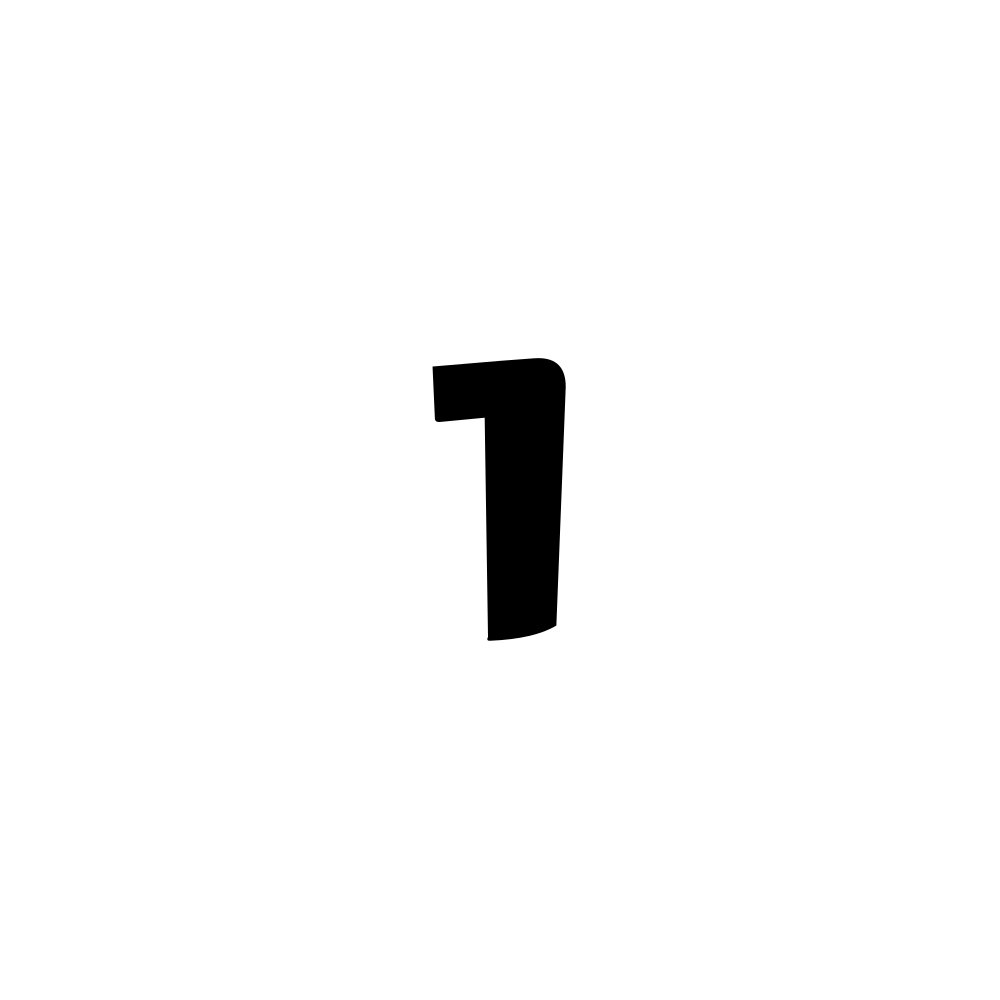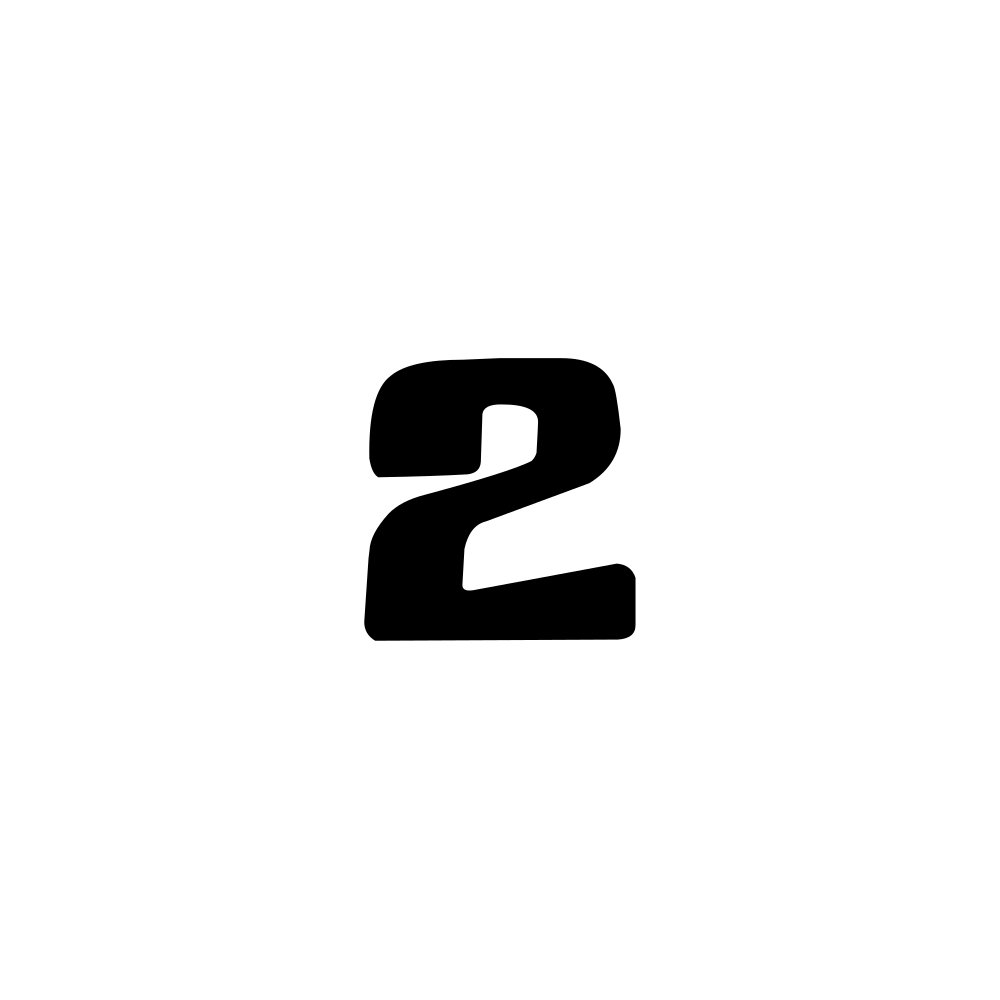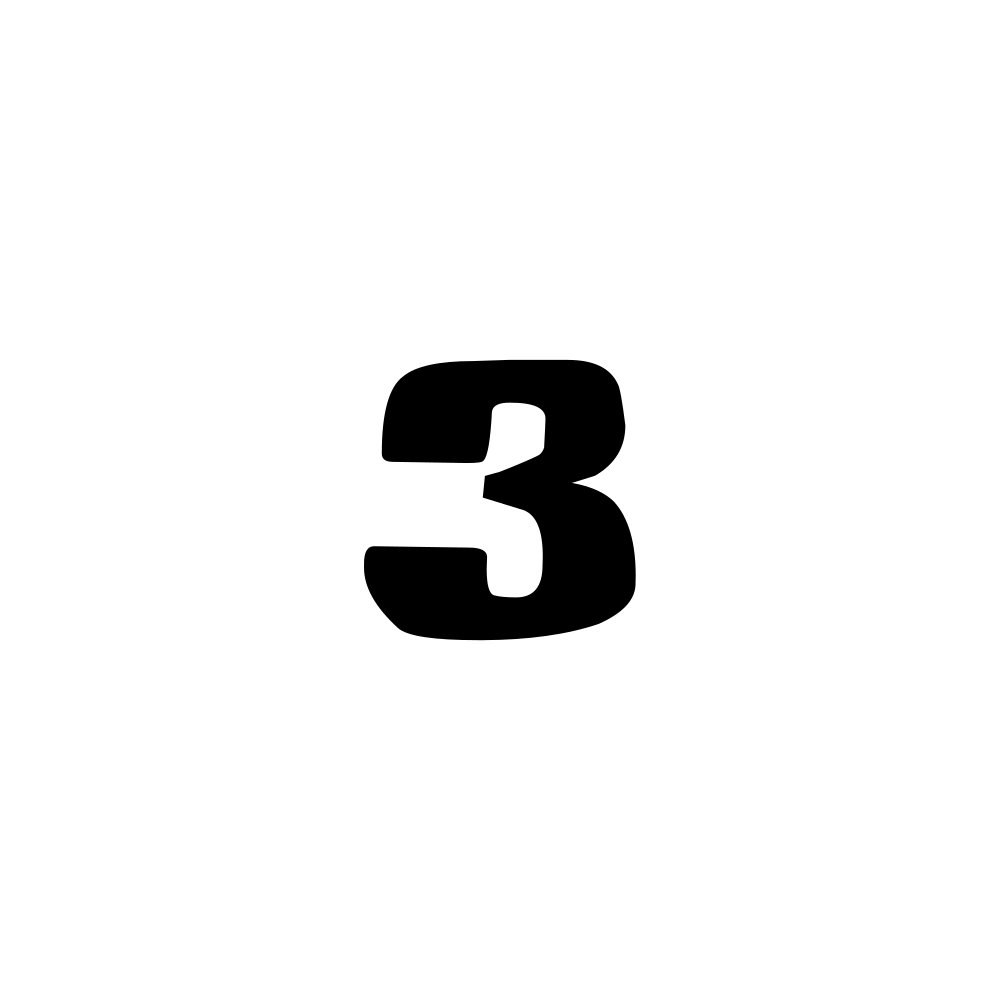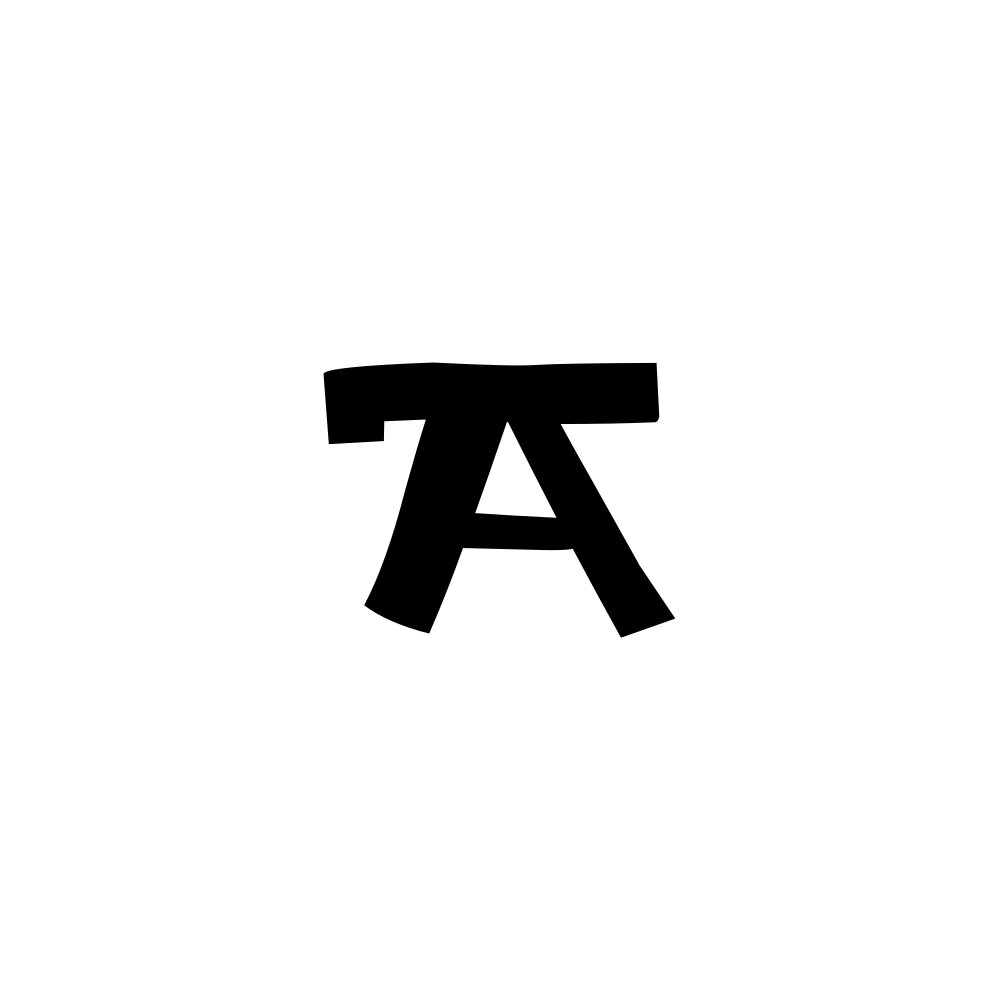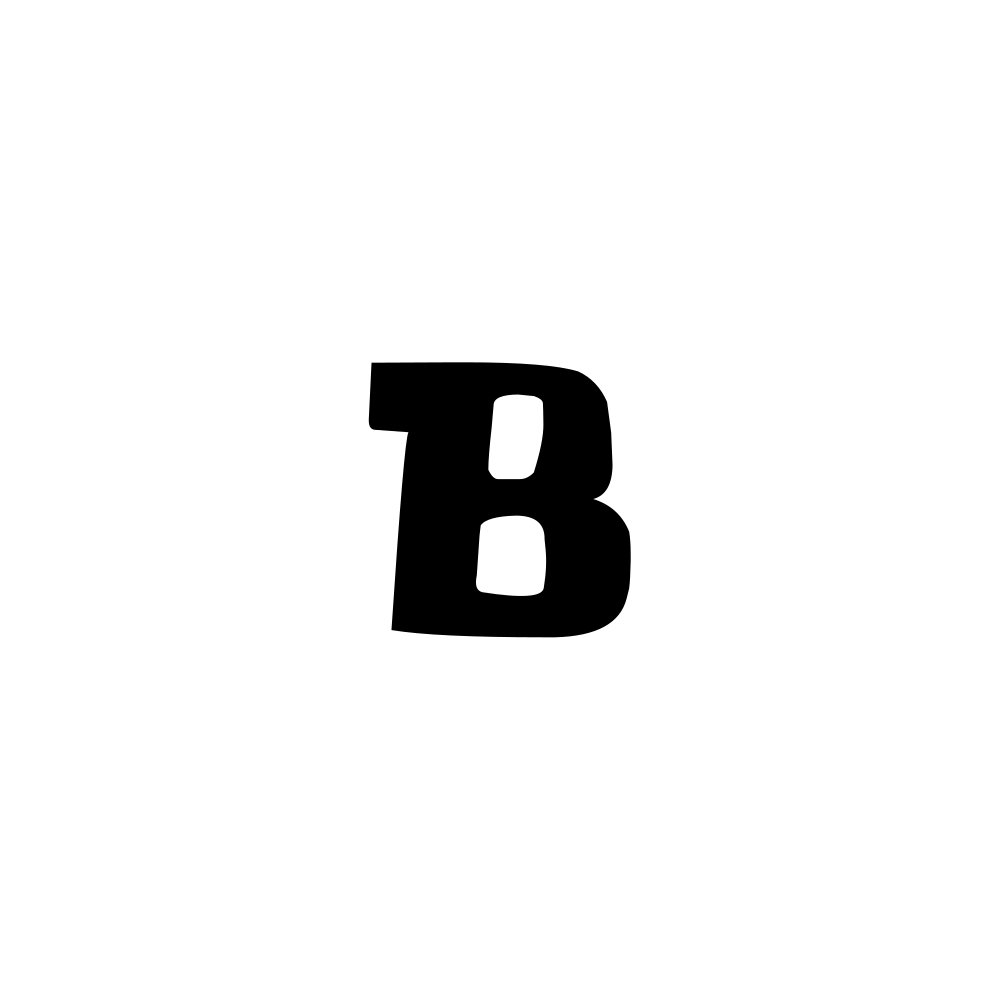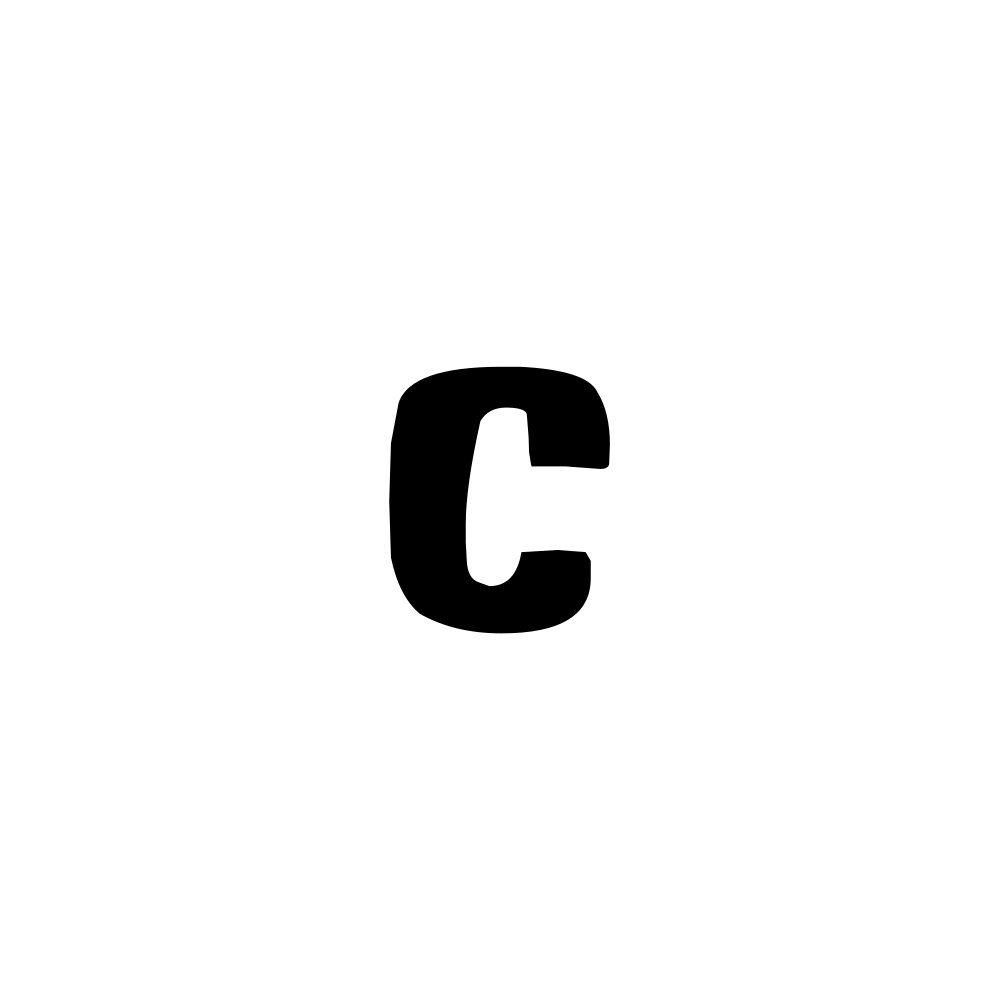
Ancient Jungle Temple Monogramm Schriftart – Tropisches Insel-Alphabet | Cricut-kompatibel
• Die Ancient Jungle Temple Monogramm Schriftart ist eine verspielte dekorative Schrift, inspiriert von tropischen Inselmotiven, alten Tempelgravuren und abenteuerlichen Dschungelthemen. Die Buchstaben besitzen kräftige Formen, abgerundete Kanten und leicht unregelmäßige Linien, die an handgeschnitzte Symbole oder traditionelle Muster erinnern. Dadurch erhält der Text einen lebendigen, abenteuerlichen Charakter und bleibt dennoch in vielen kreativen Designs klar und gut lesbar.
• Die Schrift enthält Großbuchstaben, Kleinbuchstaben, Zahlen (0–9) sowie Satzzeichen, sodass sich vollständige Wörter, Monogramme und dekorative Texte im gleichen Stil gestalten lassen. Alle Zeichen sind gleichmäßig gestaltet, damit die Schrift auch bei kleineren Projekten sauber geschnitten wird und gut sichtbar bleibt.
• Diese tropisch inspirierte Monogramm-Schrift eignet sich besonders für personalisierte Bastelprojekte, dekorative Etiketten, Kinderdesigns, Partydekorationen, Grußkarten, Sticker, Scrapbooking und viele weitere kreative DIY-Ideen, bei denen ein auffälliges und verspieltes Alphabet dem Design eine besondere Note verleiht.